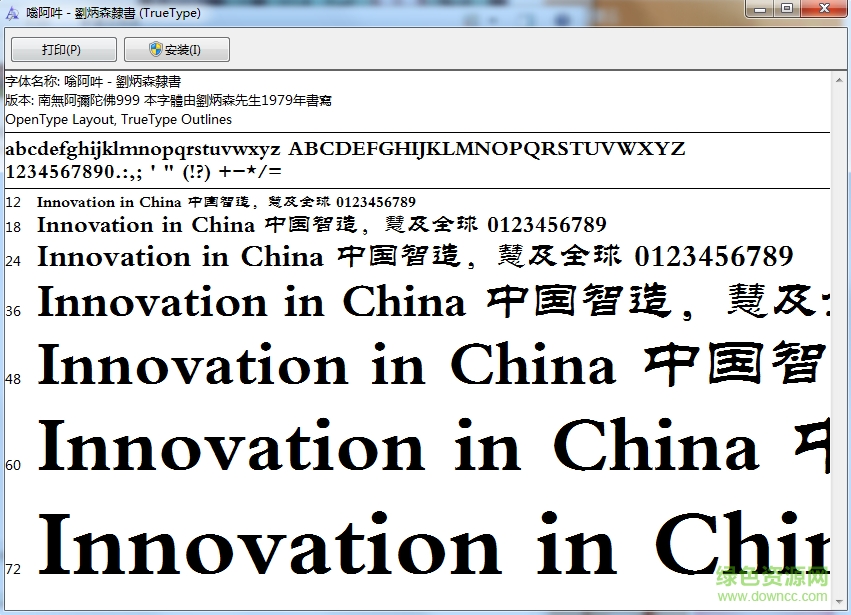
劉炳森隸書是中國(guó)當(dāng)代書法家的一款手寫書法字體,采用隸書的精髓創(chuàng)作,字跡飄逸灑脫,適用于排版印刷、書法創(chuàng)作等,歡迎來(lái)綠色資源網(wǎng)下載使用!
首先,在用筆上,劉先生講究勻凈。劉炳森隸書中很難看到飛白筆法,他似乎在極力回避這種筆法,而對(duì)線條的滋潤(rùn)、光潔有著骨子里的偏好(這很能讓人聯(lián)想起“館閣體”來(lái))。在用筆的力量分配方面,劉先生也處理得非常“公平”:橫畫一律較粗,豎畫一律較細(xì),這種筆法雖然看上去非常賣力,卻并未顯現(xiàn)出應(yīng)有的力度,究其因,主要是用筆上鋪毫與聚毫運(yùn)用不當(dāng)所致。鋪毫使線條呈扁平狀,這種線條雖然表現(xiàn)出一定的寬度,但卻喪失了應(yīng)有的厚度,缺乏立體感,給人以單薄的絲綢或布條等扁平物體的感覺(jué),而且又給人以筆始終浮在紙面上,不能入紙的感覺(jué),自然缺乏力度。聚毫所寫出的線條則相反,它表現(xiàn)出一定的立體感,給人以破空殺紙、力透紙背的審美效果。古錢幣文字就有這種審美感染力。按說(shuō),兩種筆法并無(wú)優(yōu)劣之別,關(guān)鍵是如何使用。劉先生將聚毫用在豎畫上,鋪毫用在橫畫上,橫粗豎細(xì),加劇了字形的扁平感,極大減弱了書作的體積感和感染力。
在結(jié)字上,劉炳森隸書呈現(xiàn)出“滿”的特征。無(wú)論是多筆畫字,還是少筆畫字,劉先生都將每個(gè)字處理得四角填滿。對(duì)于筆畫多的字來(lái)說(shuō),這么作要容易一些,對(duì)筆畫少的字,就需要將筆畫加粗加厚,這樣的結(jié)果便是大小齊平,如古人所謂“大字促之令小,小字展之令大”,給人的感覺(jué)便是“狀如算子”,缺乏變化、缺乏生氣、缺乏生動(dòng)活潑的氣象。